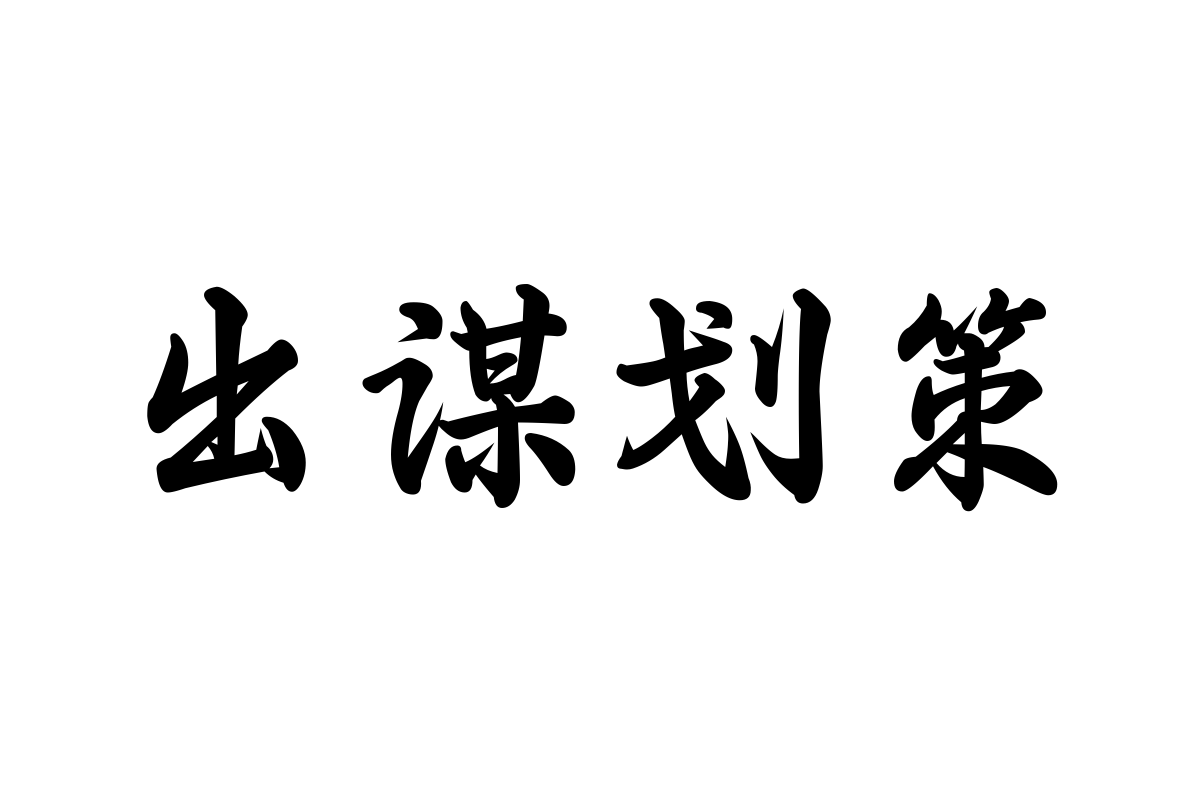
三极春联的字体介绍如下:
1. 楷体:三极春联采用了楷体,这是一种传统的中国书法字体。楷体笔画清晰、结构严谨,适合用于书写春联。在春联中,楷体的字迹显得端庄大方,寓意着新的一年里,人们的生活将如同楷书一样,规范有序,充满希望。
2. 行书:三极春联中也融入了一些行书的元素,使得整副春联既有楷体的端庄,又有行书的灵动。行书是一种介于楷书和草书之间的字体,笔画流畅、富有变化,给人以美的享受。在春联中,行书的加入,使得整副春联更加生动活泼,充满了喜庆的气氛。
3. 草书:三极春联中还巧妙地融入了一些草书的元素。草书是一种笔画简化、结构自由的字体,具有很强的个性和表现力。在春联中,草书的运用,使得整副春联更加生动有趣,充满了活力。同时,草书的加入,也体现了人们对新一年的期待和祝福,寓意着新的一年里,人们的生活将如同草书一样,充满生机和活力。
总之,三极春联的字体介绍主要围绕楷体、行书和草书这三种字体展开,通过这些字体的巧妙组合和运用,使得整副春联既庄重又活泼,既传统又现代,充分展现了中国传统文化的魅力。